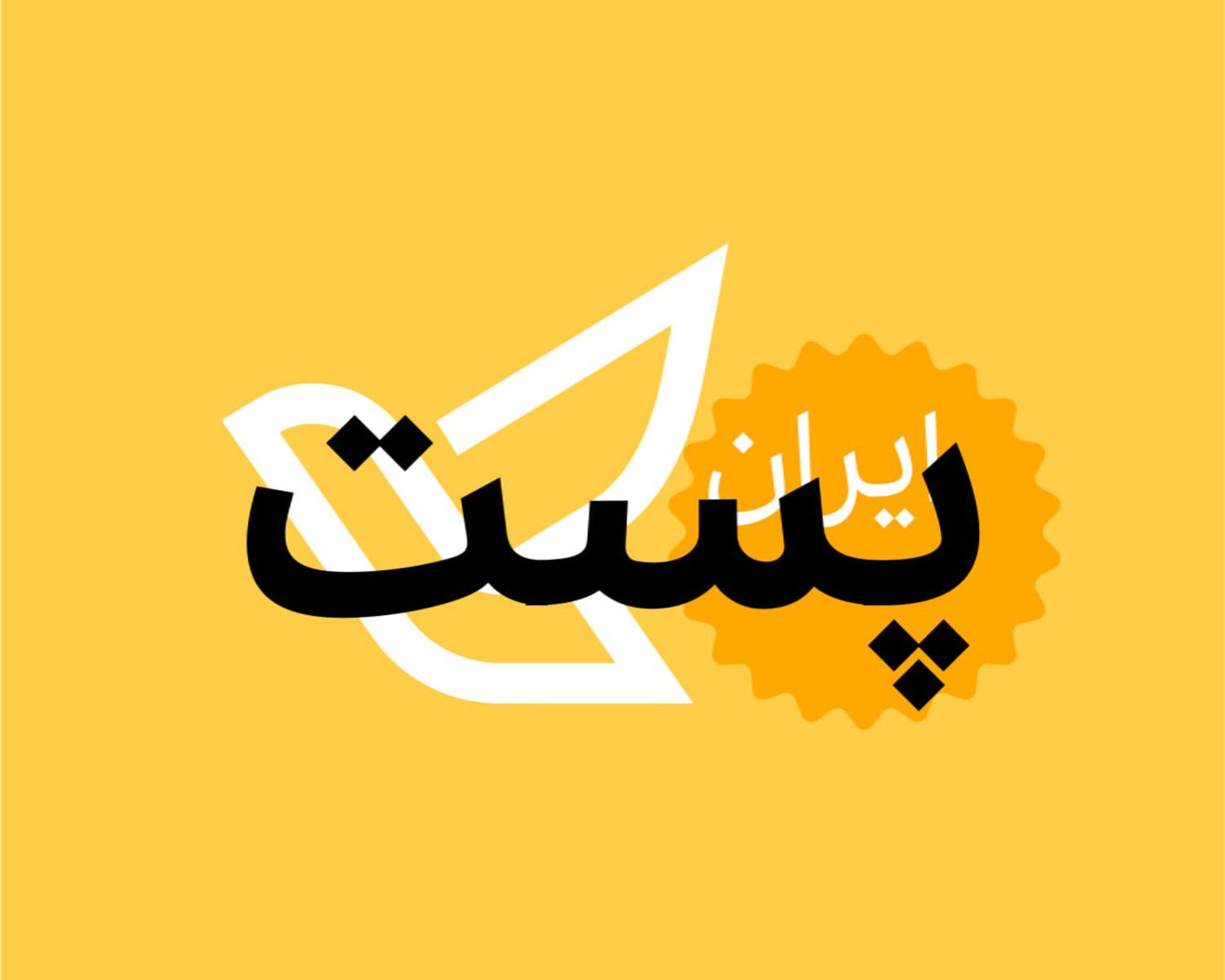
#معرفی فونت جدید پست ایران
شرکت ملی پست ایران، به عنوان یکی از قدیمی‌ترین و مهم‌ترین سازمان‌های ارائه‌دهنده خدمات پستی و ارتباطی در کشور، همواره سعی کرده است تا با توجه به نیازها و انتظارات جامعه و با استفاده از فناوری‌های نوین، کیفیت و سرعت خدمات خود را بهبود بخشد. در این راستا، شرکت پست ایران اقدام به طراحی و انتشار فونت رسمی و سازمانی جدید خود نموده است.
این فونت، یک فونت فارسی با ساختار کلاسیک و نرم است که مناسب برای استفاده در عناوین، متن‌ها، لوگوها، طراحی سایت و اپلیکیشن‌ها، اوراق بهادار و تمبرهای پستی می‌باشد. این فونت در دو وزن معمولی و بولد طراحی شده است و قابلیت تنوع و زیبایی طرح‌ها را افزایش می‌دهد. فونت پست، با توجه به مشخصات زبان فارسی و استانداردهای طراحی فونت، دارای خوانایی بالا و هماهنگی با فونت‌های لاتین است.
#هویت فونت
فونت پست ایران، نمادی از هویت و تاریخچه شرکت پست ایران است که با تلاش و همکاری گروهی از طراحان و متخصصان فونت، به وجود آمده است. این فونت، با هدف ایجاد یکنواختی و هماهنگی در تمامی ارتباطات و خدمات شرکت پست، بصورت رایگان و اختصاصی توسط این شرکت منتشر شده است و می‌توانید آن را از بخش دانلود همین مقاله و یا سایت شرکت پست ایران دانلود و استفاده کنید.
پیش‌نمایش فونت